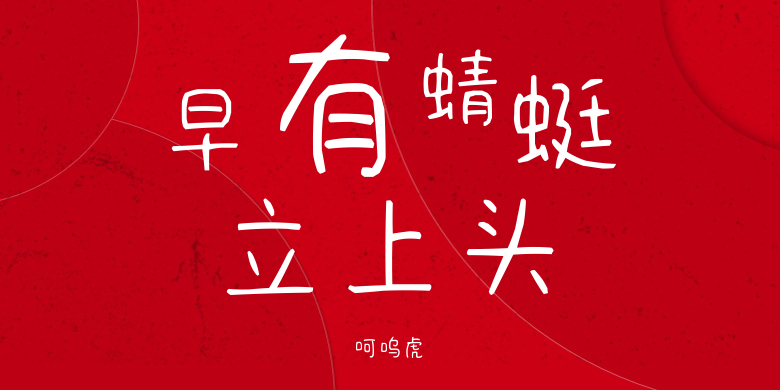
呵呜虎
呵呜虎,这款字体结构工整、笔画清晰,兼顾美观与易读性,适用于标题、正文、海报、包装、LOGO 等多种场景。字形优雅稳定,风格百搭耐看,适配日常排版与创意设计,让文字呈现更舒适、更具质感。呵呜虎一笔一画,皆是细节,以均衡的比例、流畅的线条打造舒适视觉体验,字形端正大气,风格简约现代。无论是商业设计、品牌宣传还是日常排版,都能轻松驾驭,让文字更有格调与力量。呵呜虎字体下载。